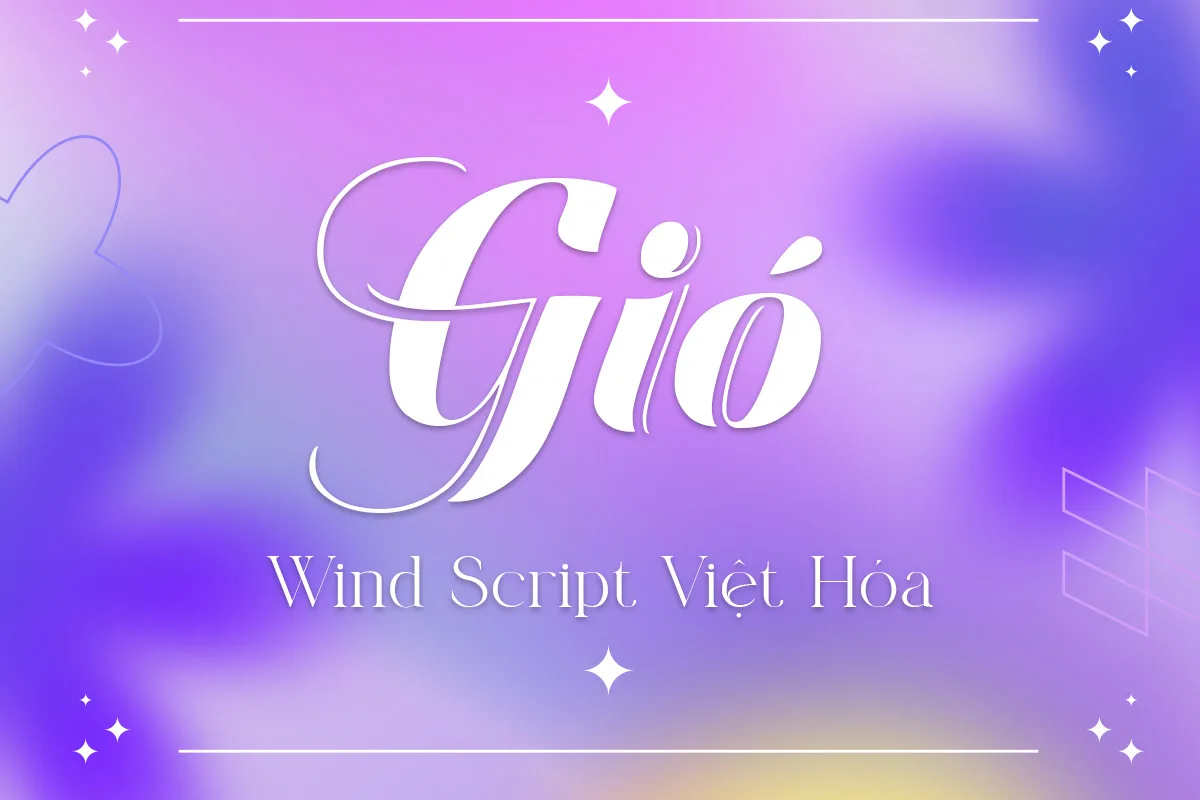
Font Wind Script Việt Hóa – Nét Đẹp Bay Bổng và Quý Phái
Wind Script Việt hóa là một kiểu chữ bay bổng mang phong cách thư pháp hiện đại, kết hợp giữa sự uyển chuyển tinh tế và độ tương phản mạnh mẽ. Những đường nét cong uốn lượn, đặc biệt ở các ký tự in hoa như “M” hay “H”, tạo nên cảm giác chuyển động như làn gió nhẹ thổi qua. Bộ font mang hơi hướng sang trọng, quý phái, rất phù hợp cho các thiết kế tiêu đề nghệ thuật, bìa sách, bao bì cao cấp hay thiệp mời cưới hỏi.
Bản Việt hóa được thực hiện trau chuốt, giữ trọn vẹn tinh thần nguyên bản trong khi bổ sung đầy đủ dấu tiếng Việt, đảm bảo sử dụng linh hoạt trong môi trường thiết kế nội địa. Wind Script không chỉ là một font chữ, mà còn là tuyên ngôn thẩm mỹ cho những ai yêu thích sự mềm mại nhưng đầy cá tính trong thiết kế.